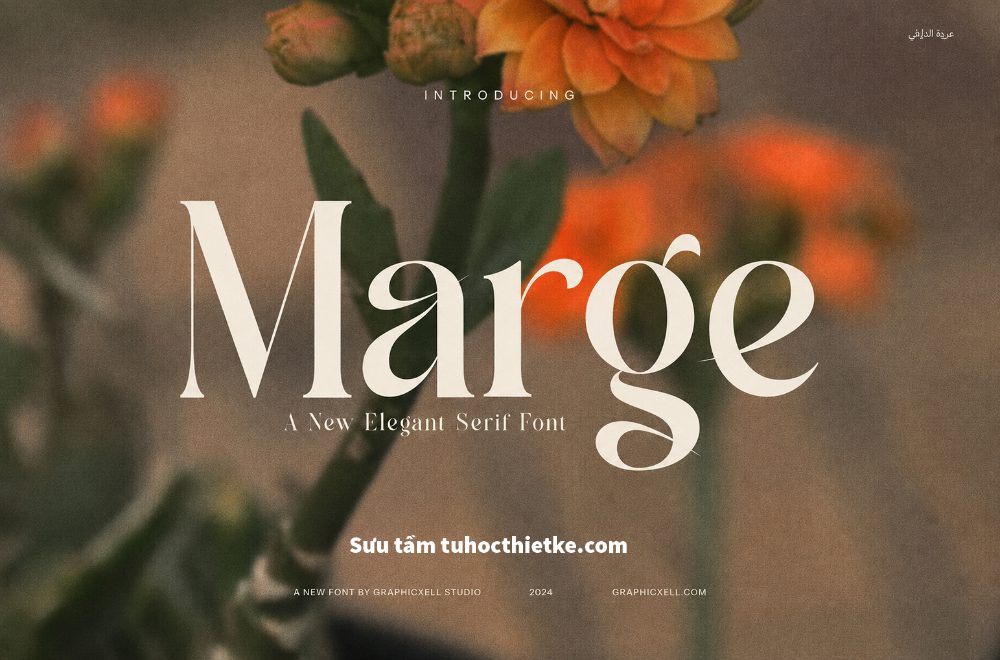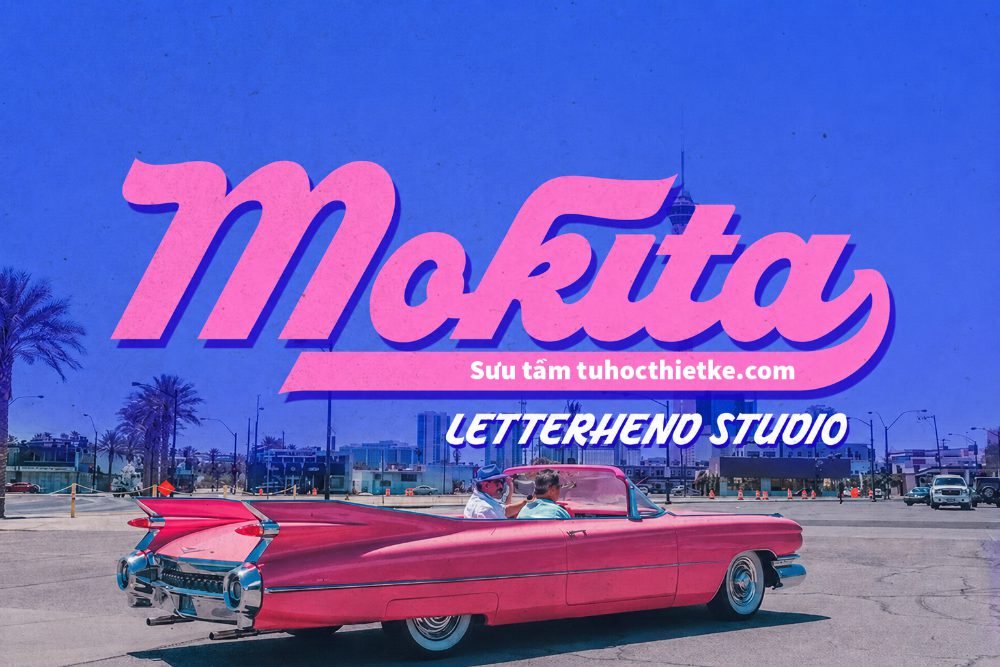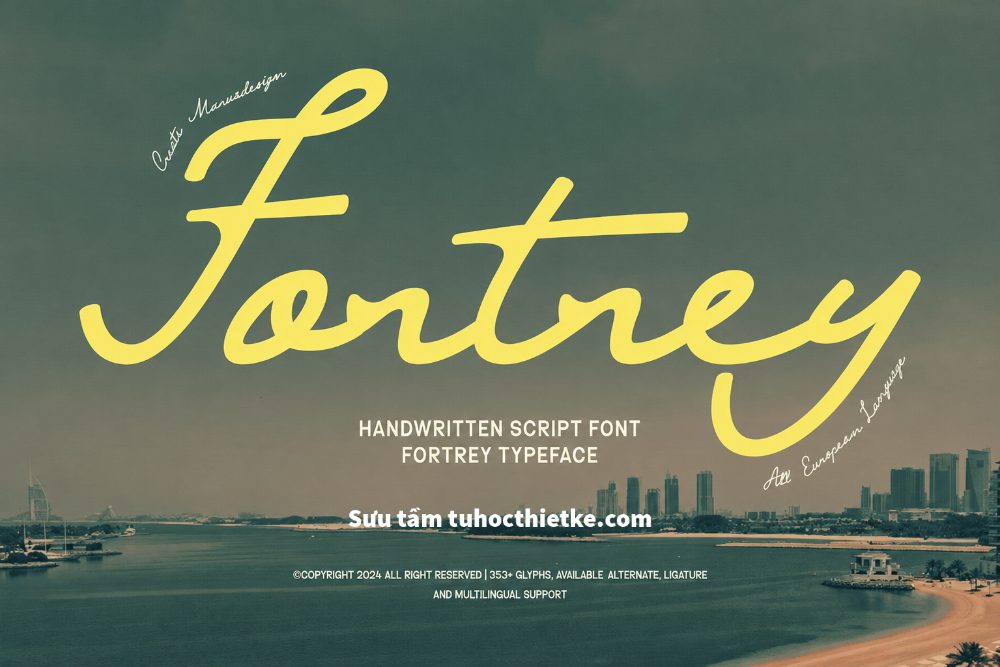
Tải Font Miễn Phí là nhu cầu rất phổ biến của designer, content creator, marketer và những người thường xuyên làm việc với hình ảnh, poster, banner hoặc các dự án nhận diện thương hiệu. Một bộ font đẹp không chỉ giúp thiết kế trở nên chuyên nghiệp hơn mà còn góp phần truyền tải đúng tinh thần, cảm xúc và phong cách của từng sản phẩm. Với 6 phông chữ có chọn lọc dành cho thiết kế, bạn có thể dễ dàng ứng dụng vào nhiều dự án khác nhau như thiết kế social media, logo, tiêu đề quảng cáo, thumbnail, poster sự kiện, brochure, catalogue hoặc các ấn phẩm truyền thông số.
Trong thiết kế đồ họa, font chữ đóng vai trò quan trọng không kém hình ảnh và màu sắc. Một font phù hợp có thể khiến bố cục trở nên hài hòa, dễ đọc và ghi nhớ hơn. Ngược lại, nếu chọn sai font, thiết kế có thể trở nên rối mắt, thiếu chuyên nghiệp hoặc không thể hiện đúng thông điệp thương hiệu. Vì vậy, việc sở hữu một bộ font được chọn lọc kỹ càng sẽ giúp designer tiết kiệm thời gian và nâng cao chất lượng sản phẩm.
Vì Sao Font Chữ Quan Trọng Trong Thiết Kế?
Font chữ là yếu tố trực tiếp ảnh hưởng đến cảm nhận đầu tiên của người xem. Trước khi đọc toàn bộ nội dung, người dùng thường bị thu hút bởi tiêu đề, cách sắp xếp chữ và phong cách typography. Một kiểu chữ mạnh mẽ có thể tạo cảm giác hiện đại, cá tính; trong khi font thanh mảnh lại mang đến sự tinh tế, sang trọng hoặc nhẹ nhàng.
Đối với các dự án thiết kế chuyên nghiệp, font chữ không chỉ dùng để hiển thị nội dung mà còn là một phần của ngôn ngữ hình ảnh. Designer cần chọn font phù hợp với lĩnh vực, đối tượng khách hàng và mục tiêu truyền thông. Ví dụ, thiết kế cho thương hiệu thời trang có thể ưu tiên font serif sang trọng hoặc sans serif tối giản. Trong khi đó, thiết kế poster âm nhạc, gaming hoặc sự kiện trẻ trung có thể dùng font display nổi bật, phá cách và giàu cá tính.
Vì Sao Font Chữ Quan Trọng Trong Thiết Kế?
Font chữ là yếu tố trực tiếp ảnh hưởng đến cảm nhận đầu tiên của người xem. Trước khi đọc toàn bộ nội dung, người dùng thường bị thu hút bởi tiêu đề, cách sắp xếp chữ và phong cách typography. Một kiểu chữ mạnh mẽ có thể tạo cảm giác hiện đại, cá tính; trong khi font thanh mảnh lại mang đến sự tinh tế, sang trọng hoặc nhẹ nhàng.
Đối với các dự án thiết kế chuyên nghiệp, font chữ không chỉ dùng để hiển thị nội dung mà còn là một phần của ngôn ngữ hình ảnh. Designer cần chọn font phù hợp với lĩnh vực, đối tượng khách hàng và mục tiêu truyền thông. Ví dụ, thiết kế cho thương hiệu thời trang có thể ưu tiên font serif sang trọng hoặc sans serif tối giản. Trong khi đó, thiết kế poster âm nhạc, gaming hoặc sự kiện trẻ trung có thể dùng font display nổi bật, phá cách và giàu cá tính.
Gợi Ý Ứng Dụng 6 Font Chữ Trong Thiết Kế
Font Cho Thiết Kế Poster Và Banner
Với poster hoặc banner quảng cáo, designer nên ưu tiên những font có độ nhận diện cao, dễ đọc từ xa và có khả năng tạo điểm nhấn mạnh. Font chữ dùng cho tiêu đề cần nổi bật, trong khi font phụ nên đơn giản để hỗ trợ nội dung chính.
Các font sans serif đậm, display hoặc condensed thường phù hợp với loại thiết kế này. Chúng giúp tiêu đề trở nên chắc chắn, rõ ràng và dễ gây chú ý khi xuất hiện trên website, mạng xã hội hoặc các nền tảng quảng cáo.
Font Cho Thiết Kế Logo Và Thương Hiệu
Khi thiết kế logo, font chữ cần có cá tính riêng nhưng vẫn đảm bảo khả năng nhận diện lâu dài. Một font quá cầu kỳ có thể gây khó đọc, trong khi font quá phổ thông lại khiến thương hiệu thiếu điểm nhấn. Vì vậy, designer nên chọn font có đường nét cân bằng, dễ tùy chỉnh và phù hợp với ngành nghề của thương hiệu.
Với các thương hiệu cao cấp, font serif hoặc font thanh mảnh có thể tạo cảm giác sang trọng. Với thương hiệu công nghệ, giáo dục hoặc dịch vụ hiện đại, font sans serif tối giản thường là lựa chọn an toàn và hiệu quả.
Font Cho Social Media Và Thumbnail
Nội dung mạng xã hội thường cần thu hút người xem trong thời gian rất ngắn. Do đó, font chữ dùng cho thumbnail, ảnh bìa hoặc bài đăng cần rõ ràng, nổi bật và dễ đọc trên cả màn hình điện thoại. Designer có thể kết hợp font đậm cho tiêu đề chính và font nhẹ hơn cho phần mô tả ngắn.
Khi Tải Font Miễn Phí cho các dự án social media, bạn nên ưu tiên font có nhiều độ dày như regular, medium, bold hoặc black. Điều này giúp việc phân cấp nội dung trở nên dễ dàng hơn và tạo bố cục chuyên nghiệp hơn.
Cách Chọn Font Chữ Phù Hợp Cho Dự Án
Xác Định Phong Cách Thiết Kế
Trước khi chọn font, bạn cần xác định phong cách tổng thể của dự án. Thiết kế hướng đến sự trẻ trung, năng động sẽ cần font khác với thiết kế sang trọng, tối giản hoặc cổ điển. Việc xác định phong cách ngay từ đầu giúp bạn chọn font nhanh hơn và tránh tình trạng bố cục thiếu nhất quán.
Ví dụ, một poster sự kiện âm nhạc có thể dùng font mạnh, phá cách và cá tính. Trong khi đó, một thiết kế cho thương hiệu mỹ phẩm nên ưu tiên font mềm mại, tinh tế và dễ tạo cảm giác cao cấp.
Ưu Tiên Khả Năng Đọc
Dù font đẹp đến đâu, khả năng đọc vẫn là yếu tố quan trọng nhất. Đặc biệt với các thiết kế có nhiều thông tin như banner quảng cáo, brochure hoặc bài đăng giới thiệu sản phẩm, font chữ cần rõ ràng và không gây khó chịu cho người xem.
Một bộ font chất lượng sẽ giúp thiết kế trở nên chuyên nghiệp, ấn tượng và truyền tải thông điệp hiệu quả hơn. Tuy nhiên, designer vẫn nên lựa chọn font phù hợp với phong cách dự án, kiểm tra khả năng đọc và lưu ý giấy phép sử dụng trước khi áp dụng vào sản phẩm thương mại. Nếu biết cách kết hợp hợp lý, những font chữ miễn phí hoàn toàn có thể trở thành công cụ mạnh mẽ giúp nâng tầm chất lượng thiết kế.